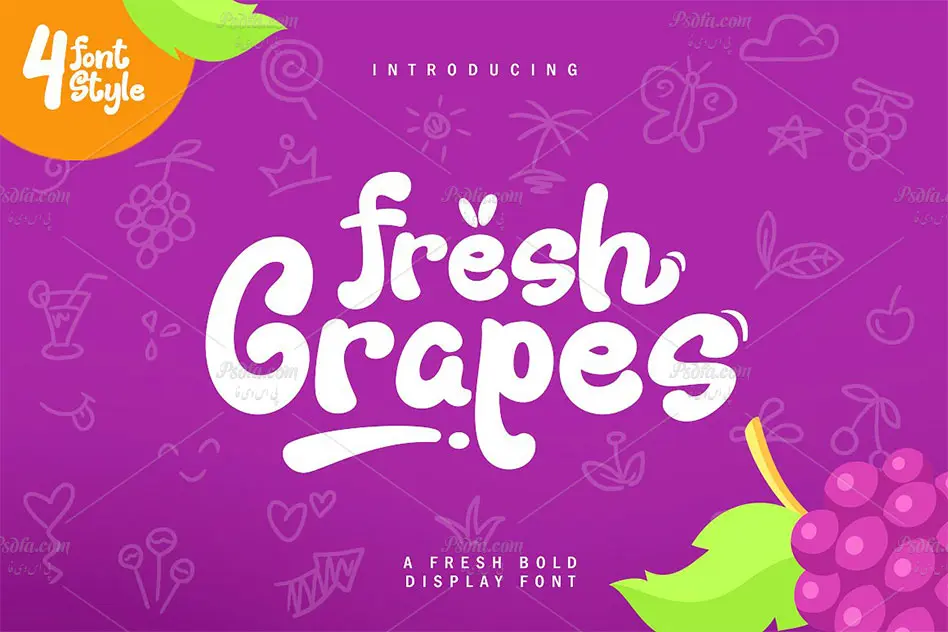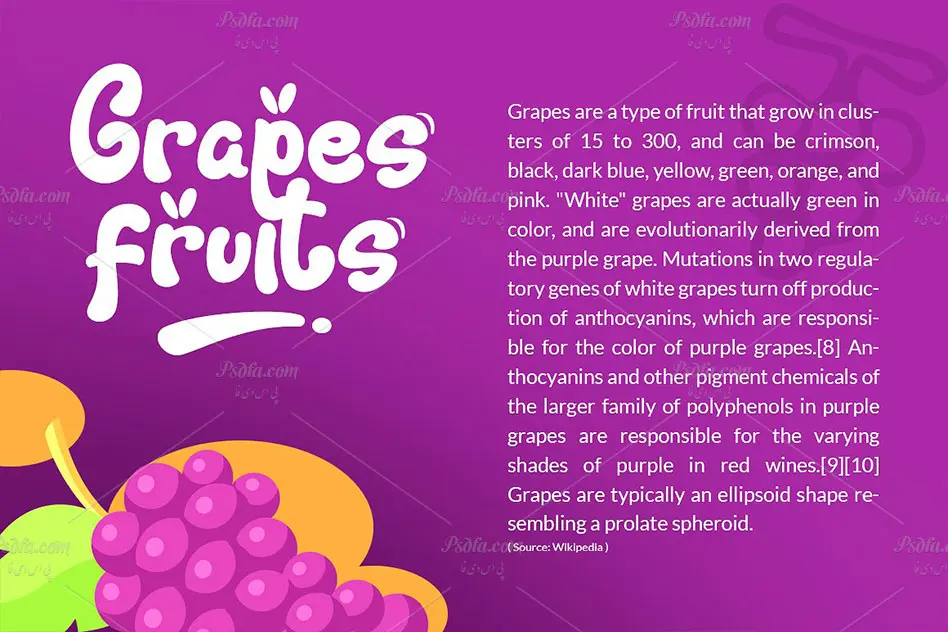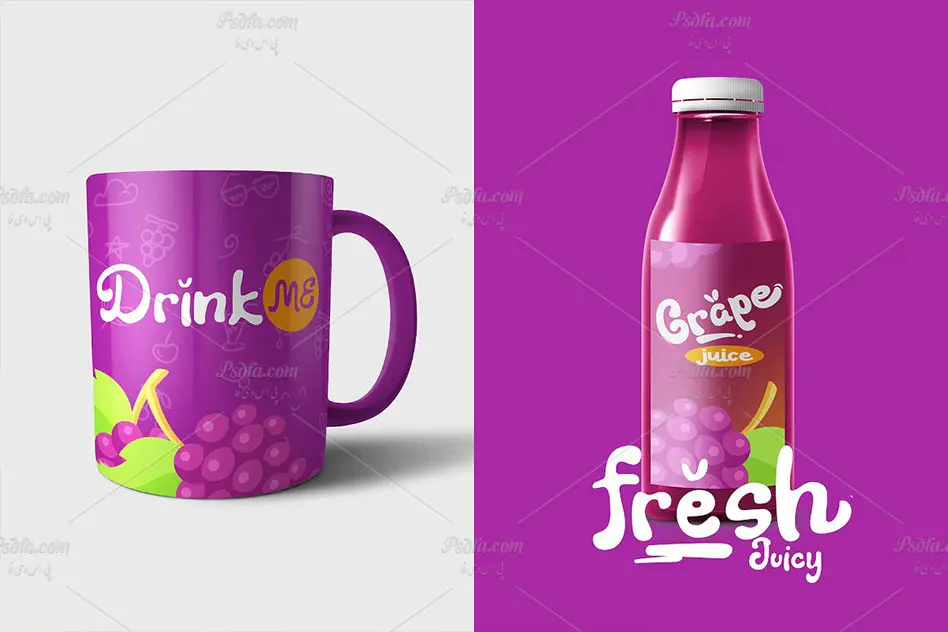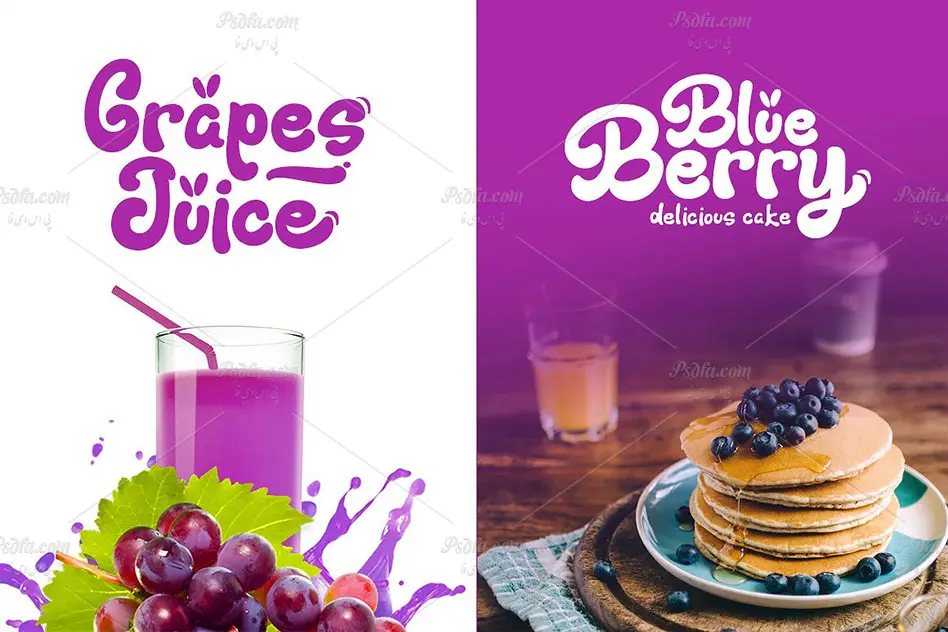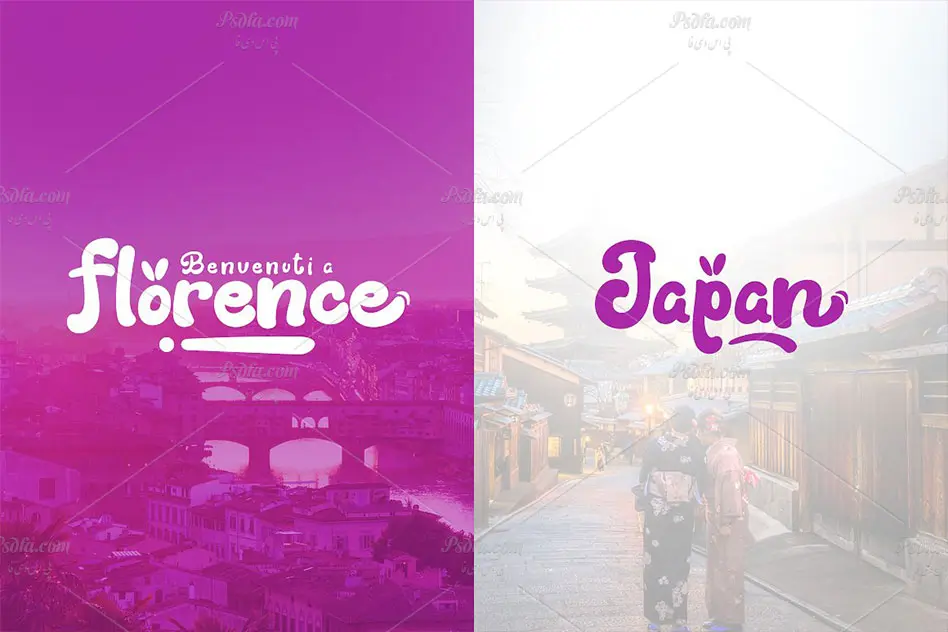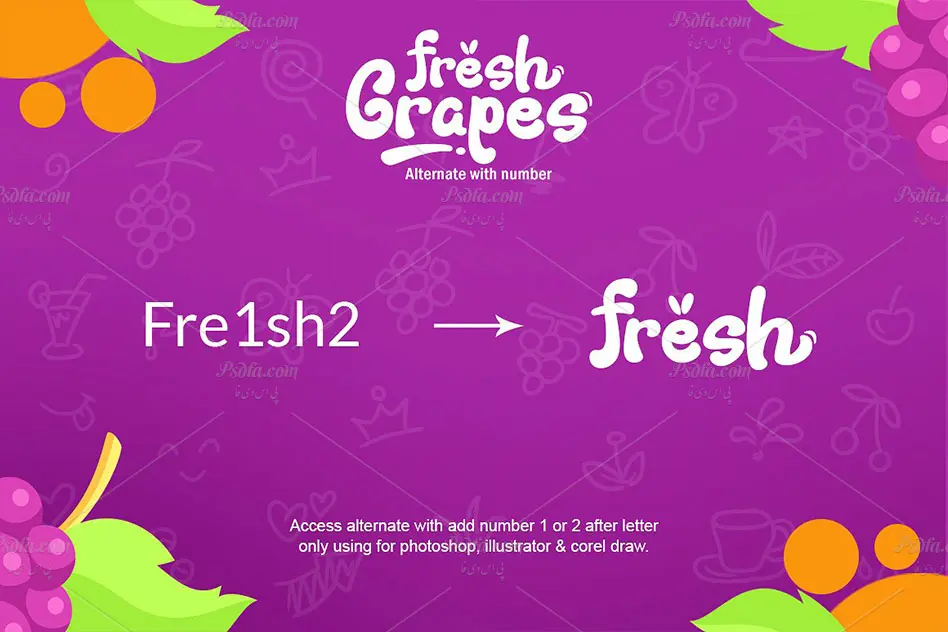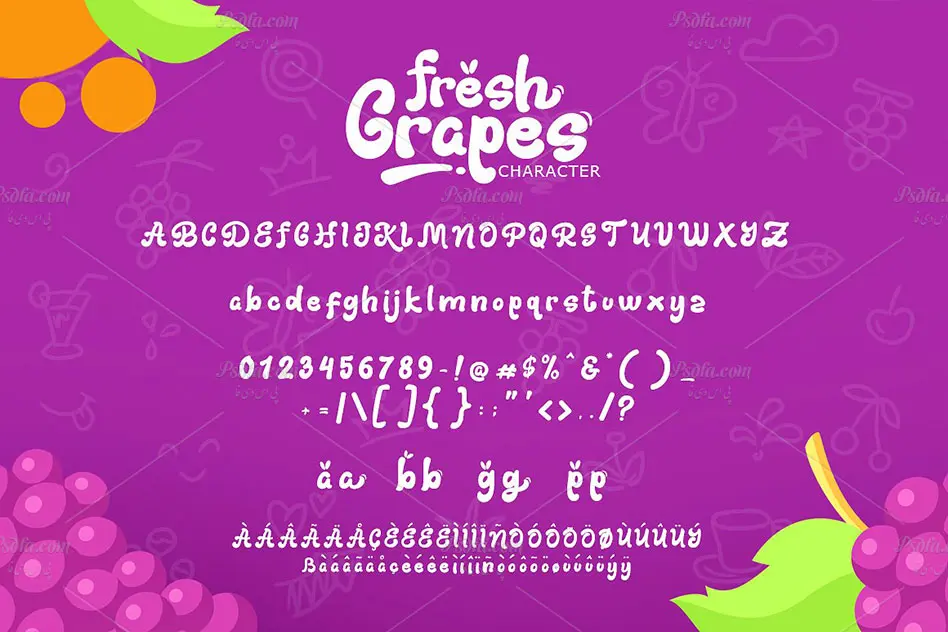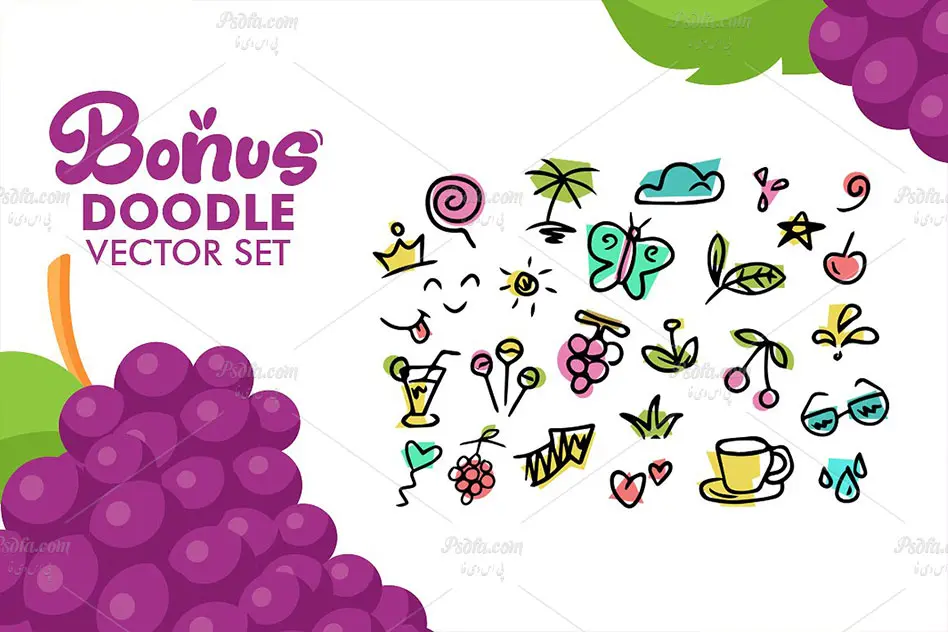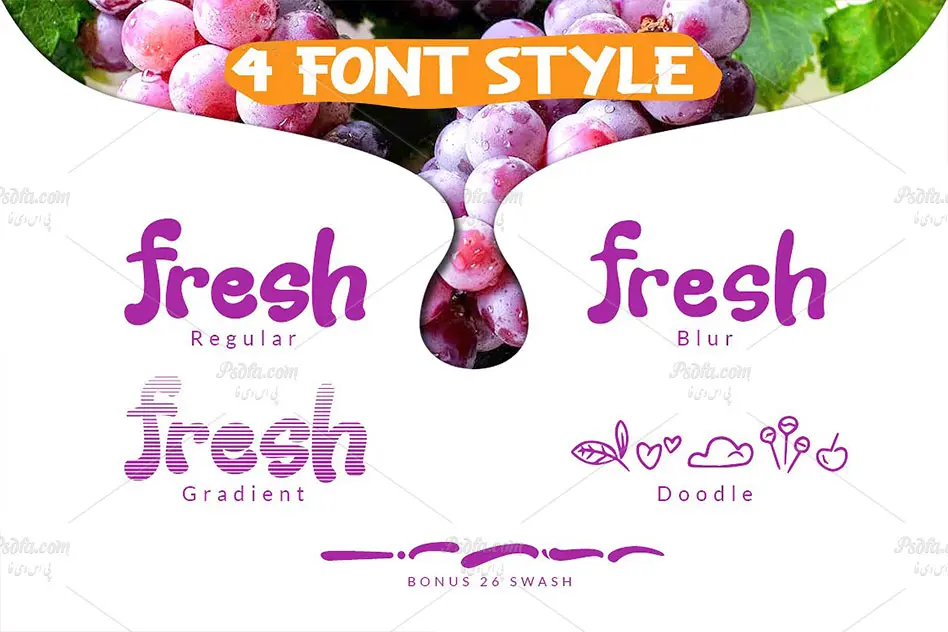
در این مطلب شاهد فونت انگلیسی فانتزی انگور تازه Fresh Grapes مناسب جهت استفاده در طراحی و گرافیک می باشید. فونت Fresh Grapes یکی دیگر از سری فونت های انگلیسی می باشد که با طرحی زیبا و در دو فرمت otf و ttf در سایت قرار داده شده است که از آن می توانید در طرح ها و پروژه های خود استفاده کنید. همچنین این فونت در 4 سبک و استایل طراحی شده است که توسط آن ها می توانید طرح هایی جذاب و خیره کننده خلق کنید. شما می توانید با نصب این مجموعه فونت در پوشه فونت های سیستم خود از آن ها به طور مستقیم در تمام نرم افزارهای گرافیکی و ویرایشگر متن از جمله نرم افزار فتوشاپ ، مجموعه نرم افزار آفیس و … استفاده نمائید. از فونت Fresh Grapes می توان در طراحی بسته بندی محصولات نوشیدنی مانند انواع آبمیوه ها ، طراحی بر روی ظروف آشپزخانه ، طراحی بر روی پارچه و لباس ، طراحی بر روی قاب و کاور موبایل و موارد دیگر استفاده کنید.